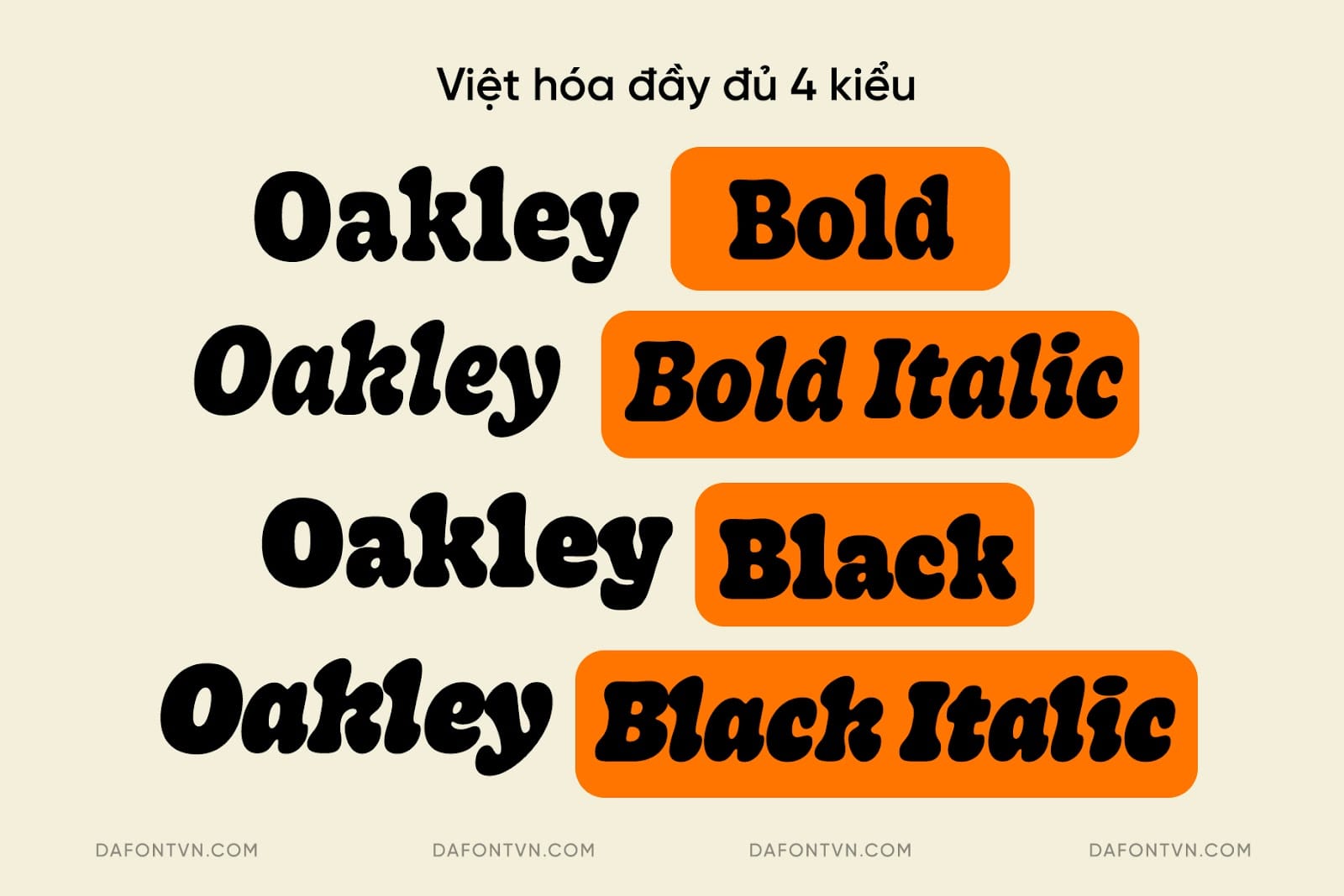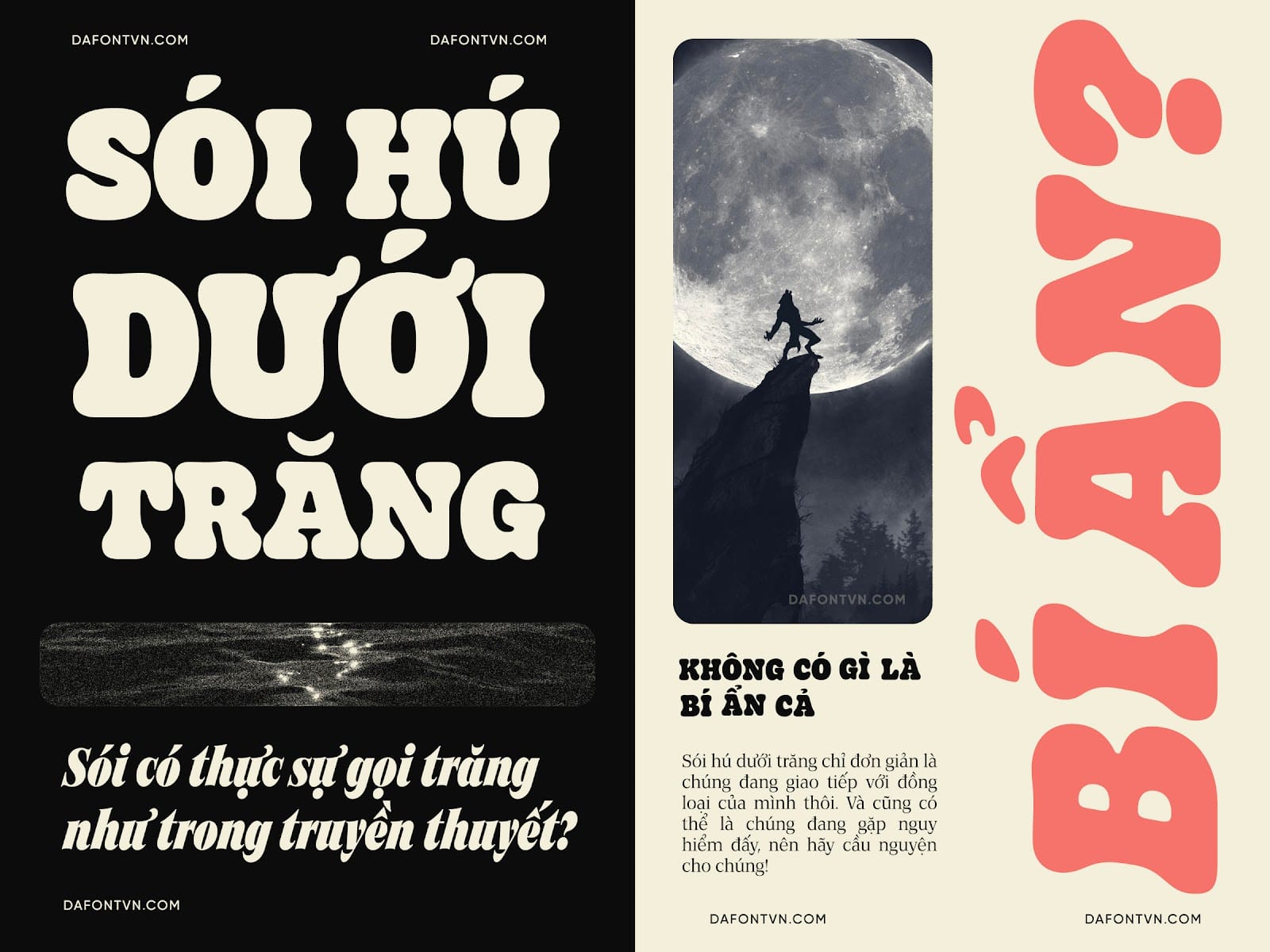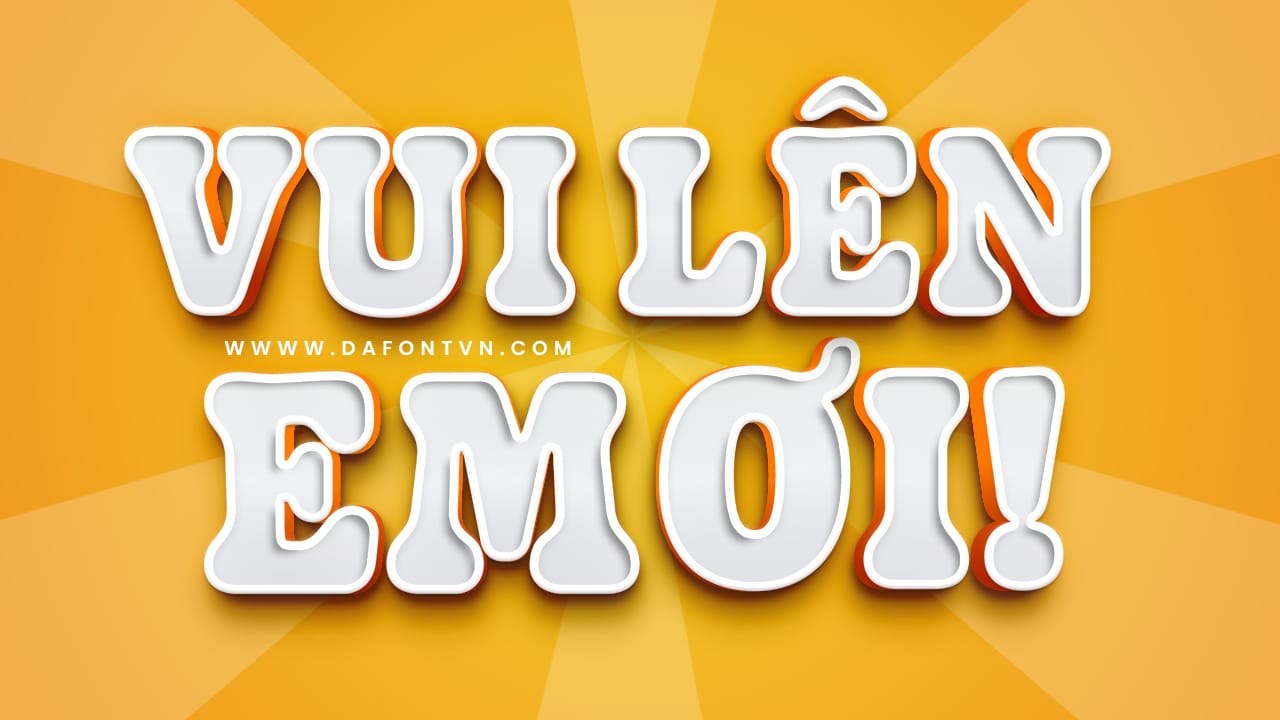
Oakley Typeface là kiểu chữ serif mang phong cách hoài cổ với đường nét mềm mại và tròn trịa lấy cảm hứng từ kiểu chữ ở những thập niên 70, 80 nhưng vẫn mang cho mình một chút hiện đại.Font chữ phù hợp cho nhiều thiết kế khác nhau như tiêu đề, bao bì, bìa sách, tạp chí, bìa album… hoặc bất kỳ thiết kế nào cần 1 kiểu chữ hoài cổ. Font được việt hóa đầy đủ 4 kiểu bao gồm (Bold, Bold Italic, Black và Black Italic).